27 meilleures polices de course ️ 2023 (gratuites et premium)
Publié: 2023-03-26Votre projet a-t-il besoin des meilleures polices de course qui donneront à votre projet un avantage concurrentiel ? Peu importe si vous concevez un logo, un site Web ou autre chose, il est important de sélectionner la bonne police qui transmet le message que vous souhaitez transmettre.
Comme il y a tellement de choix de polices sur le marché, il peut être difficile de décider laquelle correspond le mieux à vos besoins. C'est pourquoi nous avons dressé cette liste de 28 des meilleures polices de course - gratuites et premium - parmi lesquelles vous pouvez choisir en fonction de vos besoins spécifiques.
Il est indubitable que les polices de course se démarquent des autres car elles sont audacieuses et dynamiques et présentent souvent des lignes fortes et des formes angulaires nettes, vous pouvez donc les utiliser lorsque vous avez besoin de faire une déclaration. Des designs rétro classiques aux polices minimalistes contemporaines, vous pouvez trouver ici quelque chose qui répond à vos besoins.
Cet article vous aidera à trouver la police parfaite pour votre projet inspiré de la course. Nous examinerons chacune des 28 polices de la liste, vous aidant à choisir celle qui correspond le mieux à vos besoins. Alors, commençons.
Meilleures polices de course premium
Apportez la course
Bring Race est une police avec un thème de course, conçue pour être forte, rapide et puissante. Il est parfait pour les produits de course de logotype, les couvertures de jeux de course, les événements sportifs, les affiches automobiles, les couvertures de magazines automobiles, la marque, la conception de produits, les étiquettes et autres projets créatifs.
Course de pistons
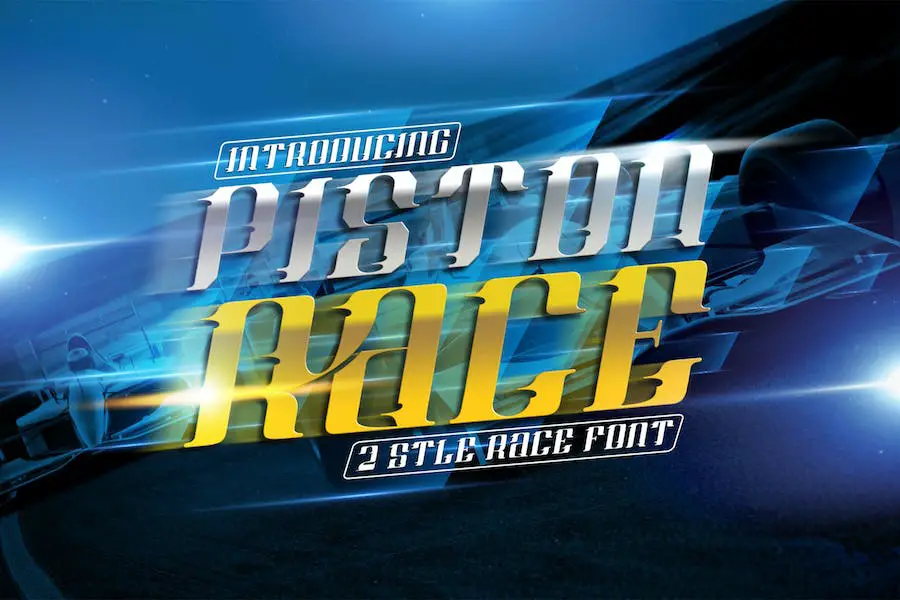
Avec sa police d'affichage de course sportive, Piston Race est une police forte et audacieuse qui est parfaite pour les conceptions de logo, les autocollants de voiture et les titres d'événements liés à la course. La police peut également être utilisée pour tout projet lié à la course.
Dans l'ensemble, Piston Race est un excellent choix si vous recherchez une police sur le thème de la course. Son apparence audacieuse et forte fera sûrement ressortir vos créations, tandis que sa facilité d'utilisation le rend accessible à tous. Alors, procurez-vous une copie et commencez à créer dès aujourd'hui !
Course difficile
Hard Race Font est idéal pour les fanatiques de course et les passionnés d'automobile. La police a un style dur et fort, parfait pour les produits de course de logotype, les événements sportifs, la marque, la conception de produits et les étiquettes.
Monstre de la course
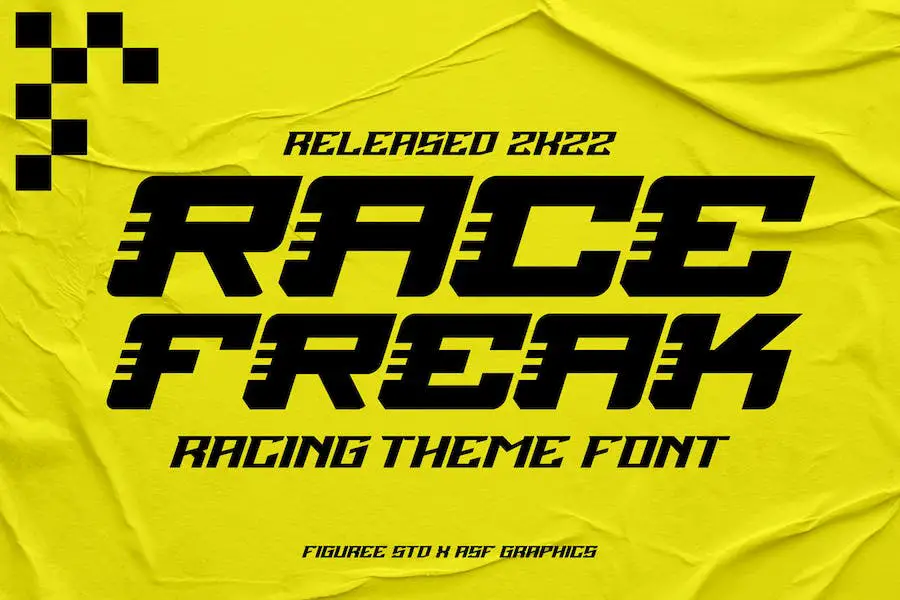
Race Freak est une police de thème de course incroyable qui possède toutes les fonctionnalités dont vous avez besoin pour créer des designs professionnels et accrocheurs. Il comprend les alphabets latins de base, les chiffres, les symboles, l'encodage PUA et la prise en charge multilingue. Race Freak est parfait pour créer des titres, des logos, une image de marque, des affiches, des emballages, de la publicité et bien plus encore.
L'une des meilleures choses à propos de Race Freak est l'encodage PUA. Cela vous permet d'accéder à des caractères spéciaux qui ne seraient normalement pas disponibles dans les polices standard. Et avec la prise en charge multilingue, vous pouvez facilement créer des conceptions dans n'importe quelle langue.